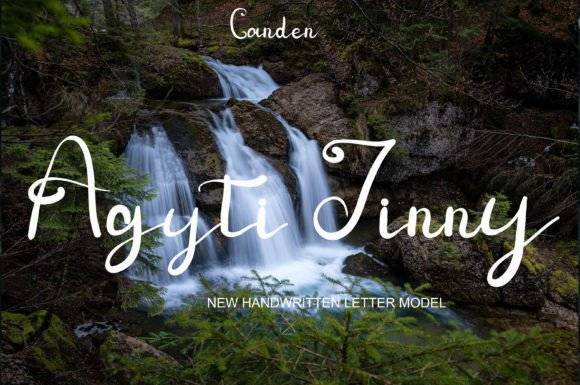
Fuente Agyti Jinny para manualidades, logotipos y proyectos de impresión
Esta fuente de estilo creativo es ideal tanto para usos artísticos como comerciales. Agyti Jinny combina curvas suaves con un diseño refinado, lo que la convierte en una excelente opción para manualidades, logotipos y diseños listos para imprimir.
Como fuente, ofrece una personalidad expresiva a la vez que mantiene una legibilidad limpia, lo que permite crear imágenes atractivas que destacan en formatos físicos y digitales. Desde invitaciones hasta recursos de marca, Agyti Jinny está lista para impulsar su flujo de diseño.
Ideal para quienes buscan infundir encanto, estilo y consistencia a sus creaciones.
Por qué te encantará
- Equilibrio entre un estilo caprichoso y profesional
- Perfecto para logotipos, papelería e impresiones.
- Bordes afilados y limpios ideales para cortar e imprimir.
- Adaptable para marca personal y empresarial.
P: ¿Qué tipo de fuente es Agyti Jinny?
A: Agyti Jinny es una fuente de exhibición elegante con energía lúdica, adecuada para manualidades, logotipos y diseños de impresión pulidos.
P: ¿Es adecuado para envases de productos impresos?
R: Por supuesto. La claridad y el carácter de la fuente la hacen perfecta para diseños de impresión y empaques de alta calidad.
| Estilo de fuente | Guión de exhibición lúdico | cursiva suelta | Serifa tradicional |